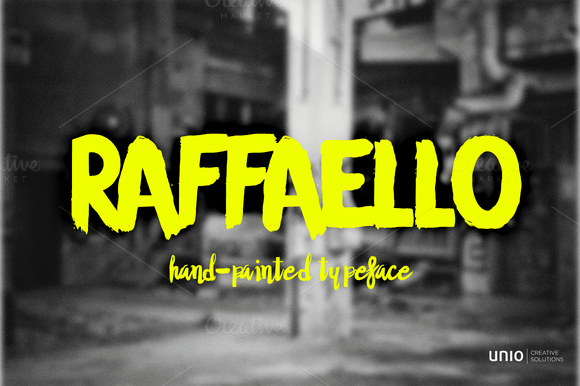
Raffaello Typeface – Download Grátis
A Raffaello Typeface é uma elegante escolha para qualquer projeto que valorize a arte do manuscrito. Inspirada nos Blackletter Fonts, essa fonte única carrega consigo uma história de letras antigas e mistério. Hamilton, o designer responsável, trouxe à luz um design que remete às épocas medievais, com seus traços levemente suaves e curvaturas delicadas, proporcionando um toque de elegância a qualquer projeto. Suas linhas sóbrias e suas formas robustas oferecem uma opção clara para aqueles buscando uma fonte que ressalta em contraste ou harmonia com outros elementos do design. Esta Raffaello Typeface não apenas retrata a versatilidade da Blackletter Fonts, mas também sua capacidade de criar um ambiente nostálgico e envolvente, onde as letras ganham vida. Seja para o uso em gráficos publicitários ou para textos formais, essa fonte manuscrita certamente enriquece qualquer projeto com seu charme e história.